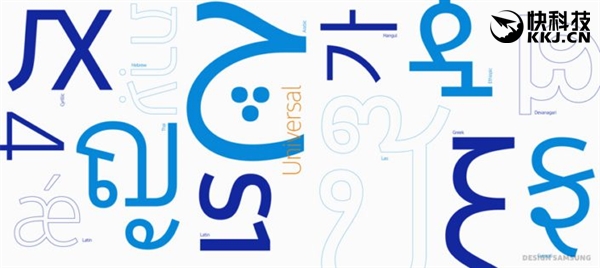
三星发布自主字体SamsungOne:全平台通用
导语Google、苹果之后,三星也设计了一套完全属于自己、全面代表自我形象的字体,命名为“SamsungOne ”,未来三星旗下硬件设备、软件应用等等都会统一使用这套字体。这套字体覆盖了26套书写系统、400多种语言、25000多个符号 ,是三星联合设计工作室Brody Associates以及一批字体专家共同制作的。字体设计遵循了五个核心原则:人文主义(Humanist)、易区分(Distinctive)、通用性(Universal)、专业性(Expert)、清晰易读/可扩展...
Google、苹果之后,三星也设计了一套完全属于自己、全面代表自我形象的字体,命名为“SamsungOne ”,未来三星旗下硬件设备、软件应用等等都会统一使用这套字体。
这套字体覆盖了26套书写系统、400多种语言、25000多个符号 ,是三星联合设计工作室Brody Associates以及一批字体专家共同制作的。
字体设计遵循了五个核心原则:人文主义(Humanist)、易区分(Distinctive)、通用性(Universal)、专业性(Expert)、清晰易读/可扩展(Legible/Scalable)。
三星表示,该字体不仅适合智能手机、智能手表等小型设备,还会出现在产品包装、宣传海报上 ,但不清楚会首先用在什么地方,手机、电视、笔记本、平板机、微波炉、烤箱等等都有可能。